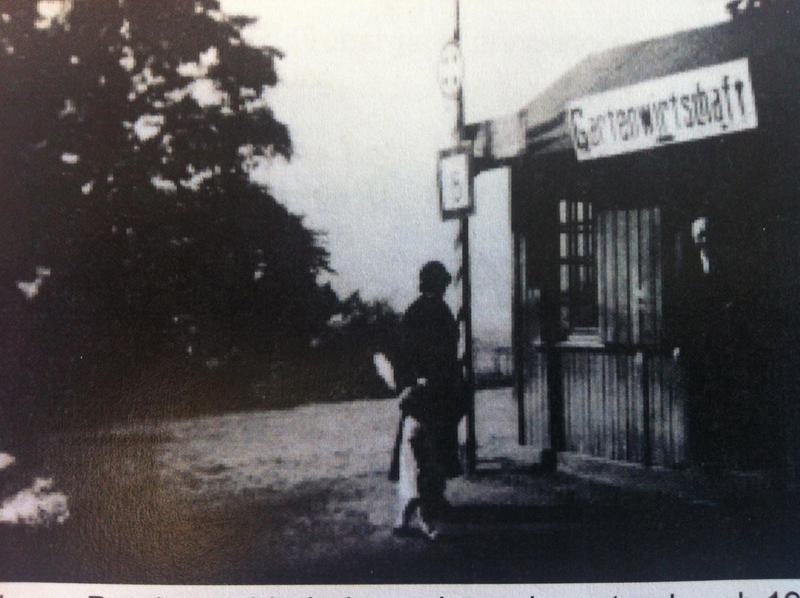
Schriftart aus Foto um 1927 gesucht
habt ihr eine Ahnung, welche Schrift bzw. welcher Schriftstil das Wort "Gartenwirtschaft" auf diesem Bild ist?
Das ist handgemalt. Schriftstil: Grotesk, soweit man hier überhaupt etwas erkennen kann, mit leichten Rest-Einflüssen des Jugendstil auf die Proportionen.
Das ist handgemalt. Schriftstil: Grotesk, soweit man hier überhaupt etwas erkennen kann,
Ist da was mit dem ch gemacht worden, Ligatur oder so?
In der Tat, das Bild ist ziemlich mau ...
Lässt sich mit Angabe der Lokalität vielleicht ein besseres Bild im Netz finden?
Bei "optisch ähnlich" meint Google wohl leider, das abgebildete wäre ein Auto ;-)
Leider sind keine anderen Archivbilder vorhanden.